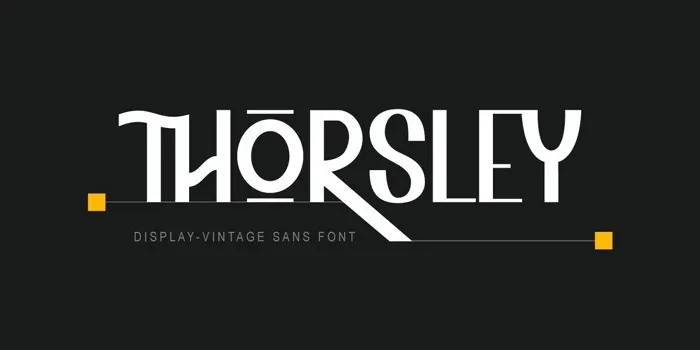
Thorsley Display Font – Download Grátis
Thorsley Display Font é uma fonte moderna que traz elegância em cada caractere. Esta fonte se destaca por sua aparição contemporânea, desportiva e robusta. Ela remete ao futuro tecnológico e à fascinante poética do design gráfico. É perfeitamente adaptável para anúncios, logotipos e qualquer projeto que busque uma combinação de modernidade sofisticada e criatividade surpreendente. Seja em um website ou material impresso, Thorsley Display Font é uma ótima opção para levar o seu design ao próximo nível.
Designer: tigade-std